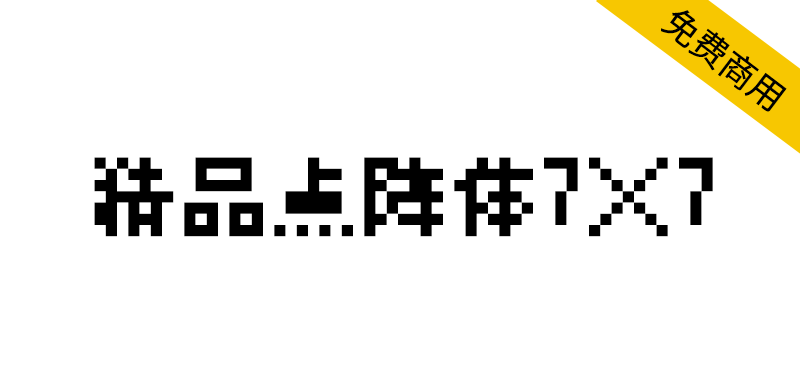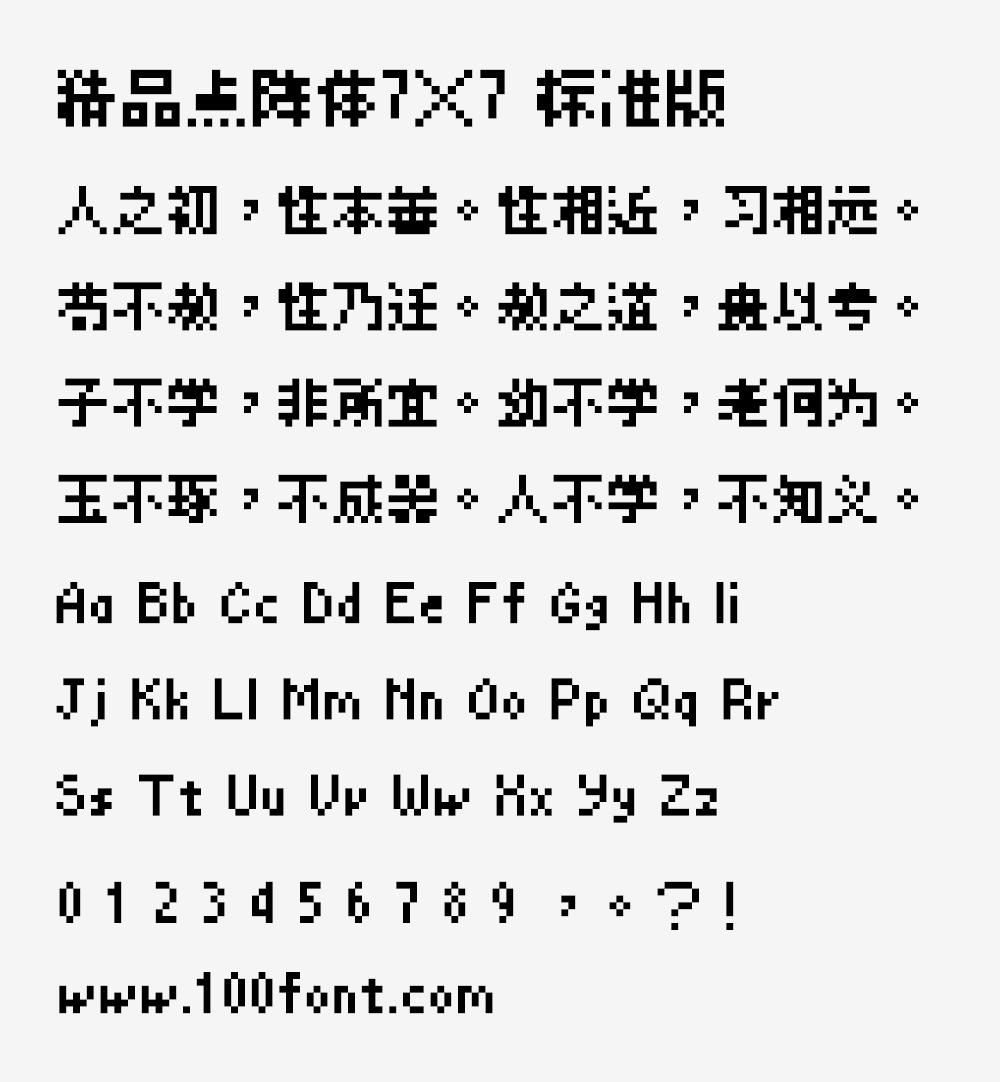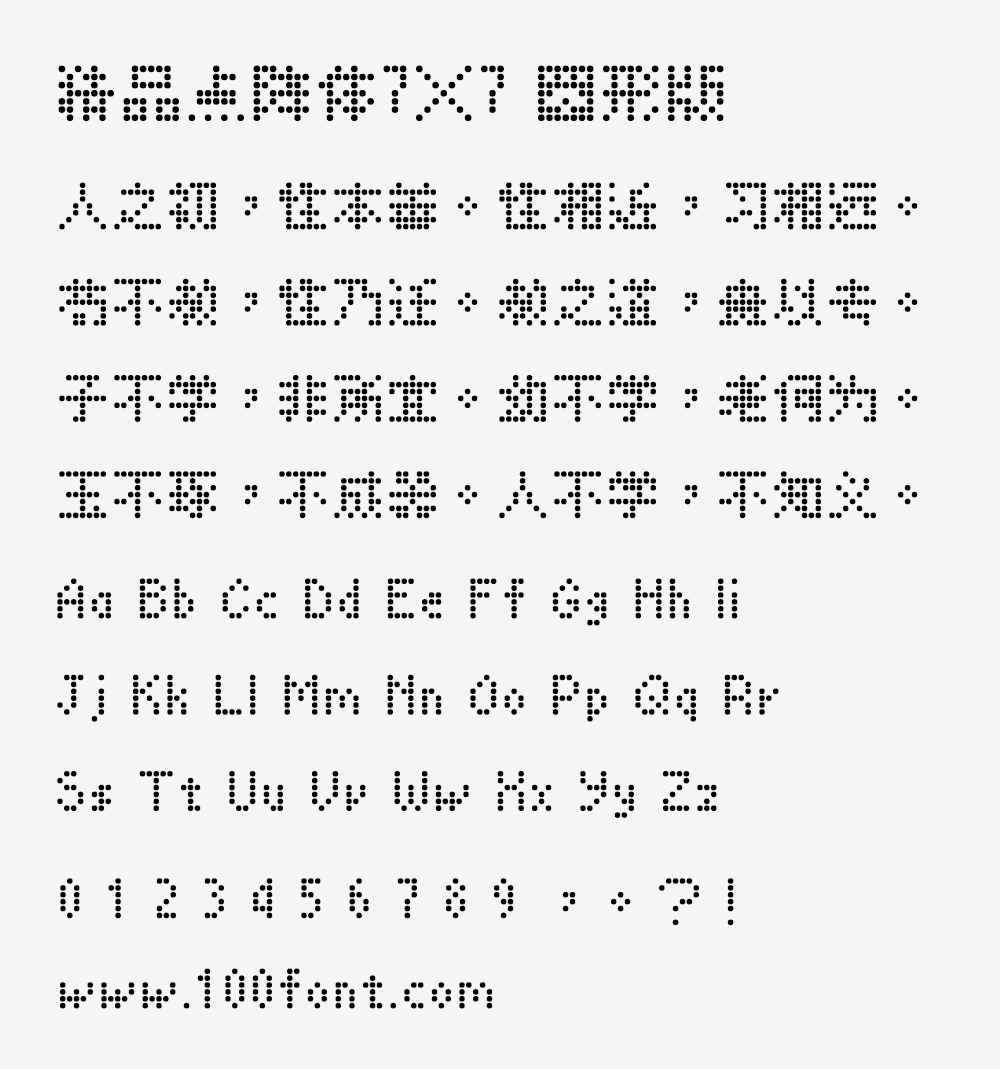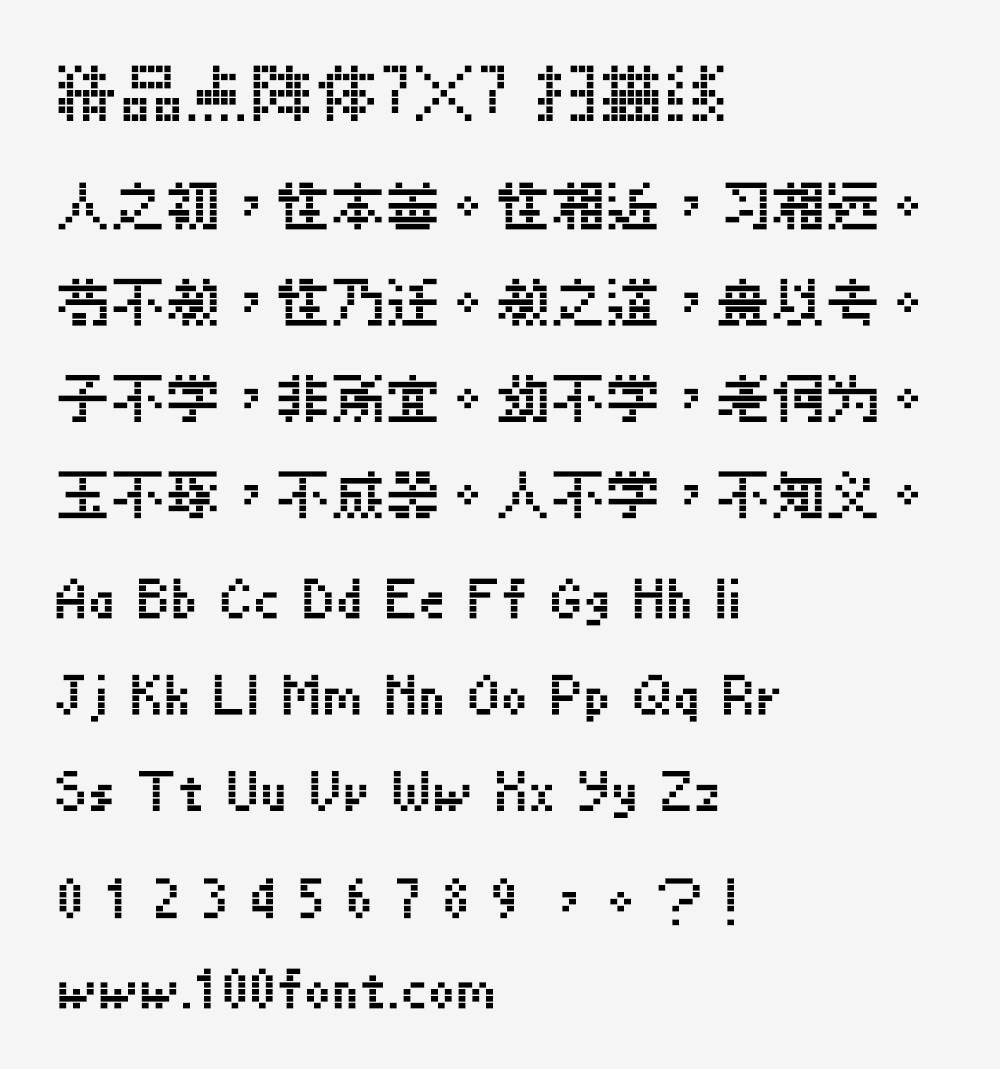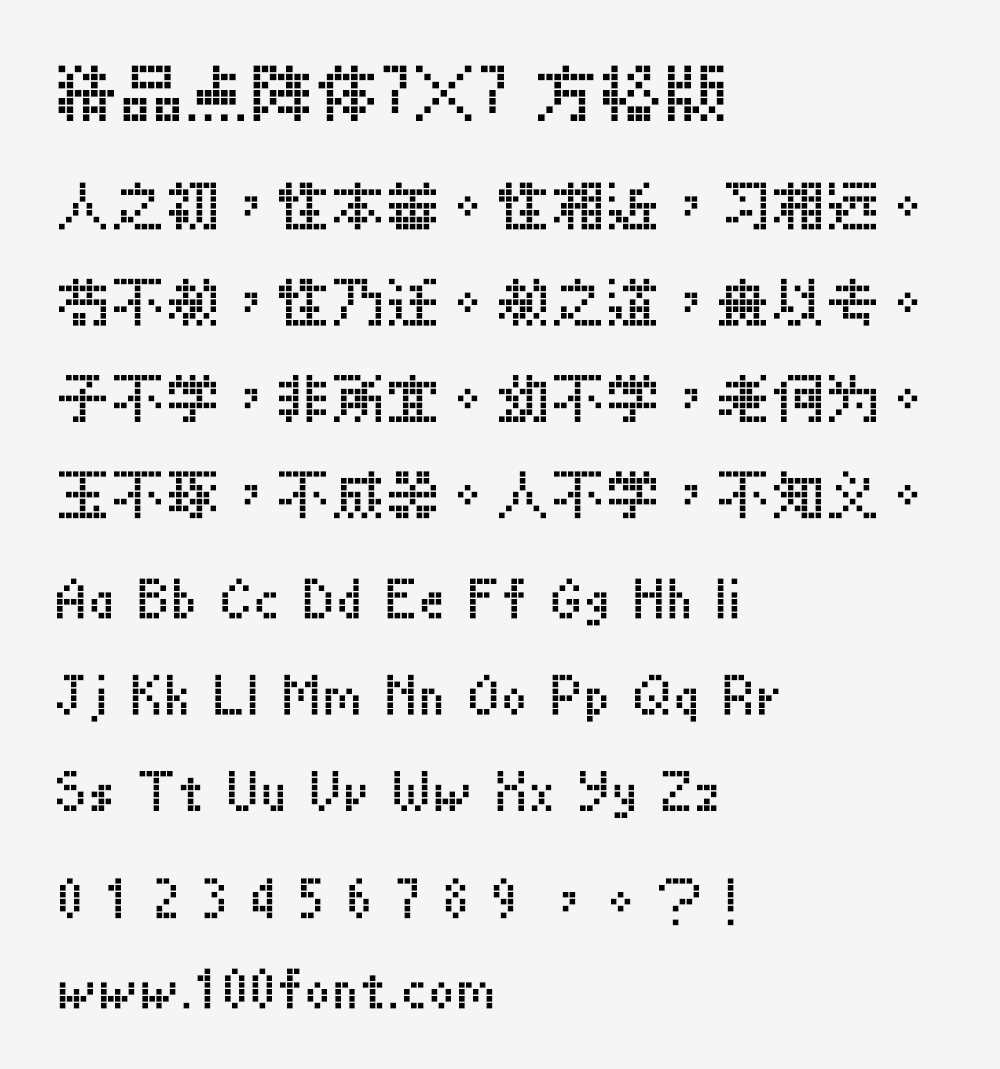
【精品点阵体7×7】免费、开源、有趣的点阵字体
精品点阵体7×7 (BoutiqueBitmap7x7) 是一款基于美咲フォント改作的字型,目的为适合在繁体中文环境中使用。我们改正了一些标点符号、日本习惯写法、增加大量字符,使字型使用更方便! 这是一款带有极强烈的点阵风格的字型,非常适合用在像素画、游戏相关主题等等。
注意:精品点阵体7×7标准版的简体和繁体字符都非常全,但是方格版、扫描线版、圆形版的简体字符不是很全,可能会出现缺字,更适合应用于繁体场景。